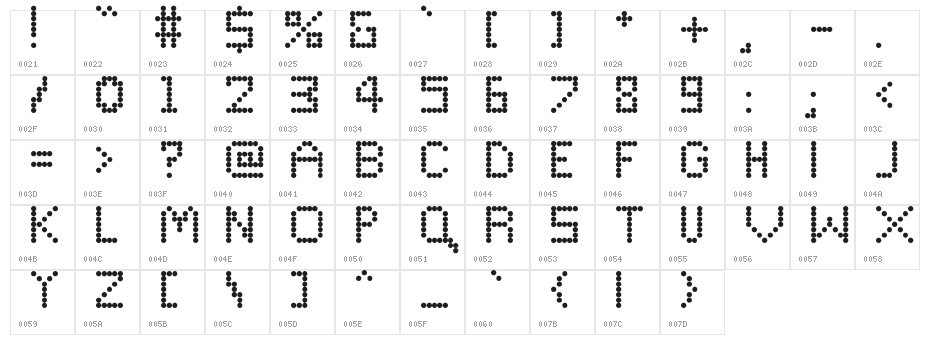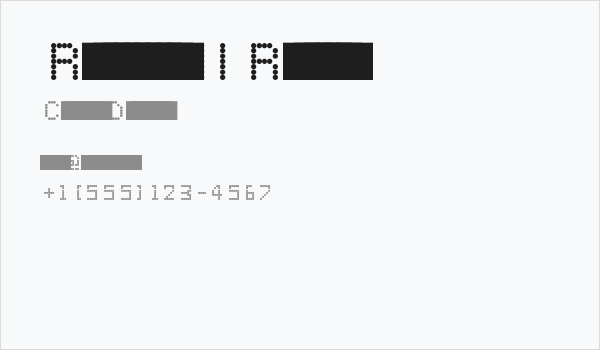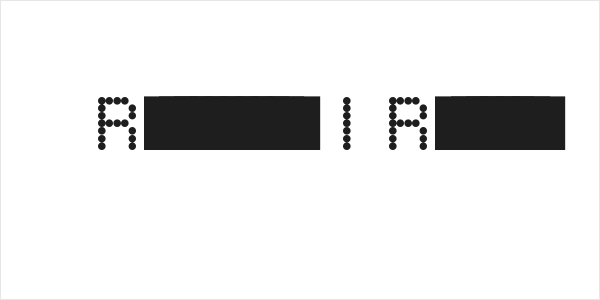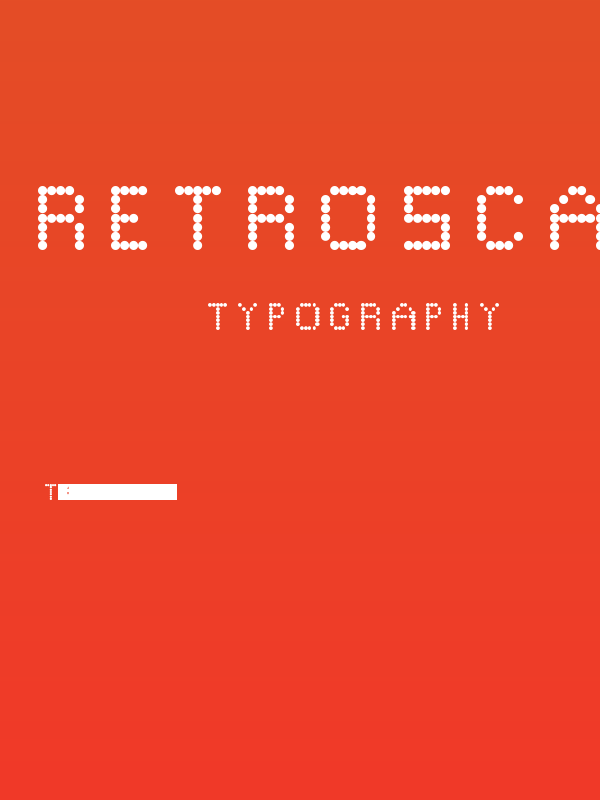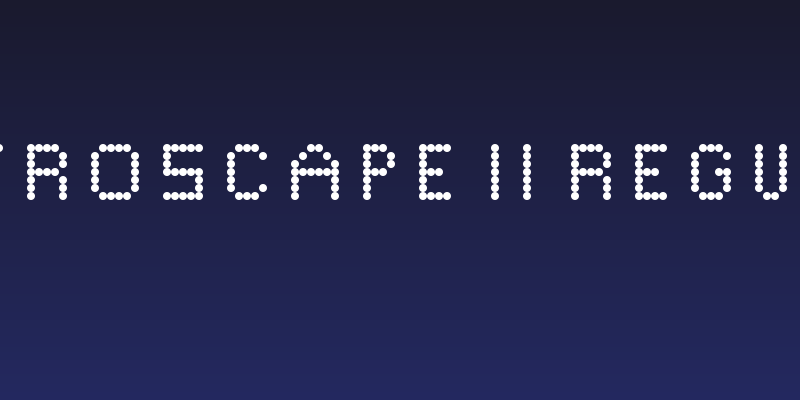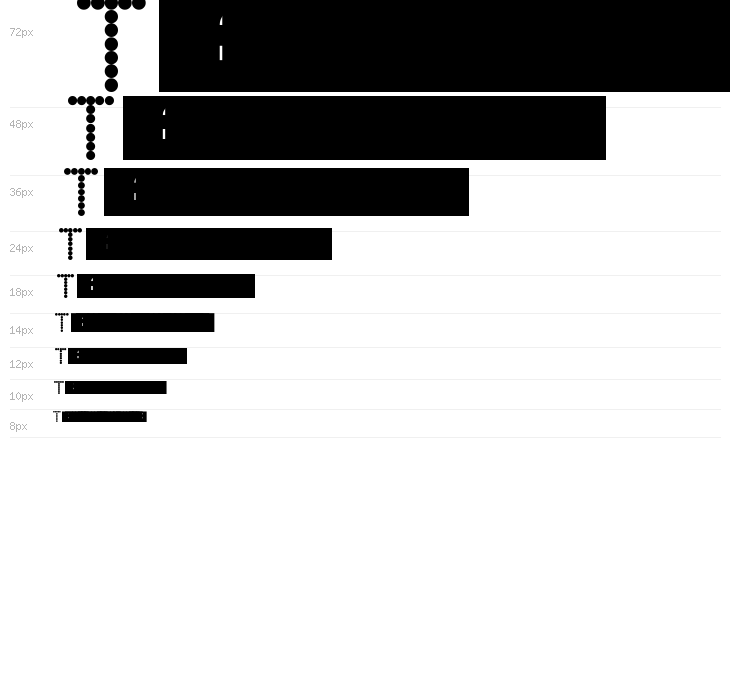
Retroscape II Regular Font
| Gesamtstil | Retro, Digital |
| Anwendungsfall | Headlines, Logos, Digital displays |
| Vorgeschlagene Projekte | Ideal for retro-themed designs, digital displays, arcade game graphics, and futuristic branding. |